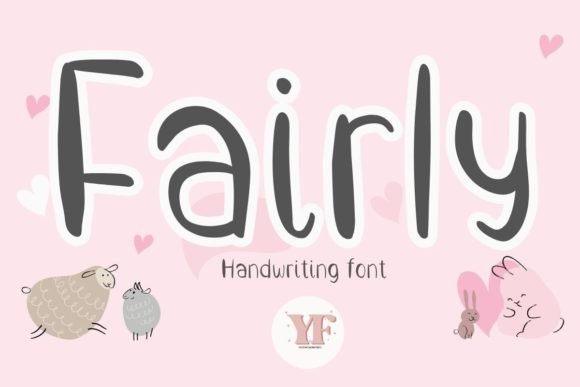
Fairly
Ulasan Lengkap: Font Fairly – Keanggunan Tulis Tangan yang Memikat
Jika Anda mencari font yang memadukan sentuhan seni tangan dengan nuansa akademik yang santai, Fairly adalah pilihan yang sempurna. Dibuat dengan cermat, font ini menggabungkan keindahan desain manual dengan kebebasan penulisan yang mengundang. Apapun kebutuhan desain Anda—dari logo, heading, hingga materi pemasaran—Fairly mampu mengubah setiap teks menjadi pernyataan keotentikan yang menarik.
Karakteristik Utama Fairly
- **Kesan Tulis Tangan yang Natural:** Setiap huruf menyerupai tulisan tangan bebas, sehingga menciptakan nuansa kasual namun tetap elegan.
- **Keterbacaan Tinggi:** Meskipun memiliki gaya unik, font ini tetap mudah dibaca pada ukuran kecil maupun besar.
- **Versatilitas Desain:** Cocok untuk berbagai aplikasi—pemasaran digital, cetak, atau presentasi—tanpa kehilangan keaslian.
- **Keharusan Kreatif:** Menambahkan sentuhan personal tanpa mengorbankan profesionalisme.
Manfaat Menggunakan Fairly dalam Proyek Anda
Dengan Fairly, Anda dapat:
- Meningkatkan **daya tarik visual** pada materi iklan.
- Menekankan **keaslian merek** melalui gaya tulisan yang unik.
- Menumbuhkan **koneksi emosional** dengan audiens lewat kesan personal.
Kesimpulan
Fairly adalah font yang menggabungkan keanggunan seni tangan dengan kemudahan penggunaan dalam dunia desain modern. Tekankan identitas merek Anda dengan gaya yang santai namun profesional. Pilih Fairly untuk memberikan sentuhan estetika yang tak terlupakan pada setiap proyek.